Descarga 7 geniales tipografías modulares
Descubre y descarga estas tipografías modulares que diseñaron jóvenes creativos en formación
Juan Ortega (@ortegadesign) es un diseñador gráfico graduado en la Escuela Superior de Diseño de Madrid. Está especializado en branding, packaging, editorial, tipografía y diseño web, y ha trabajado para clientes como ALD Automotive, Banco Santander, Iberdrola, Movistar, Real Madrid CF y SEAT, entre muchas más.
Además, ha dedicado parte de su labor profesional en la docencia en la Escuela Artediez de Madrid. En 2015, impartió un taller sobre tipografía modular, del cual derivaron proyectos de tipografía que Juan decidió compartir con la comunidad de Domestika.
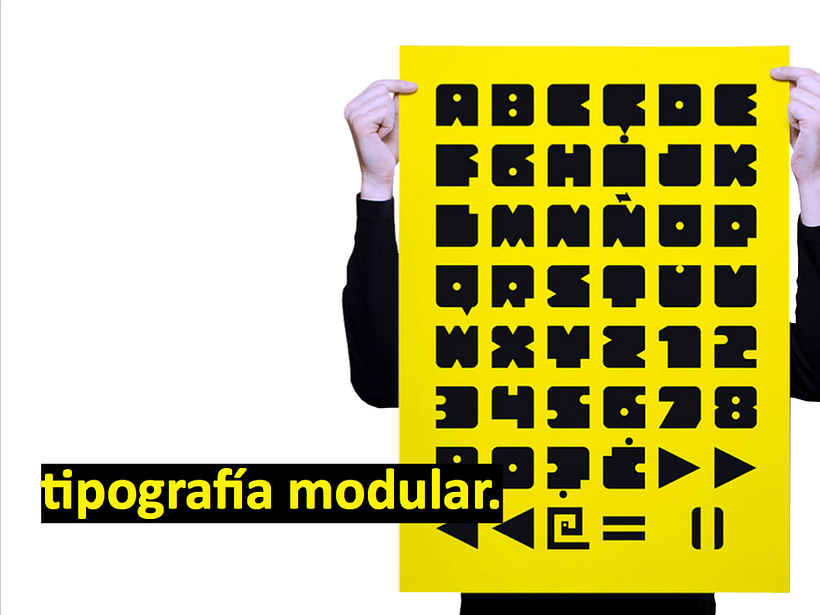
Tipografía modular
La tipografía modular consiste en construir alfabetos a partir de módulos y formas preconstruídas. Además, ofrece amplias posibilidades vinculadas a la comunicación del mensaje en el ámbito del diseño gráfico. Para Juan, es el punto de partida y la base inicial a la comprensión del mundo de la tipografía, así como la puerta a la formación de ideas en la imaginación o en el pensamiento del diseñador gráfico para la construcción de ideas más complejas.
El proyecto que Juan ha compartido es una recopilación de los trabajos de estudiantes que practicaron estas ideas de manera didáctica, con un carácter público y sin ánimo de lucro. Las tipografías finales fueron digitalizadas por ellos mismos con un programa online gratuito llamado Fontstruct.
Iris TTF
Por Iris Mogollón
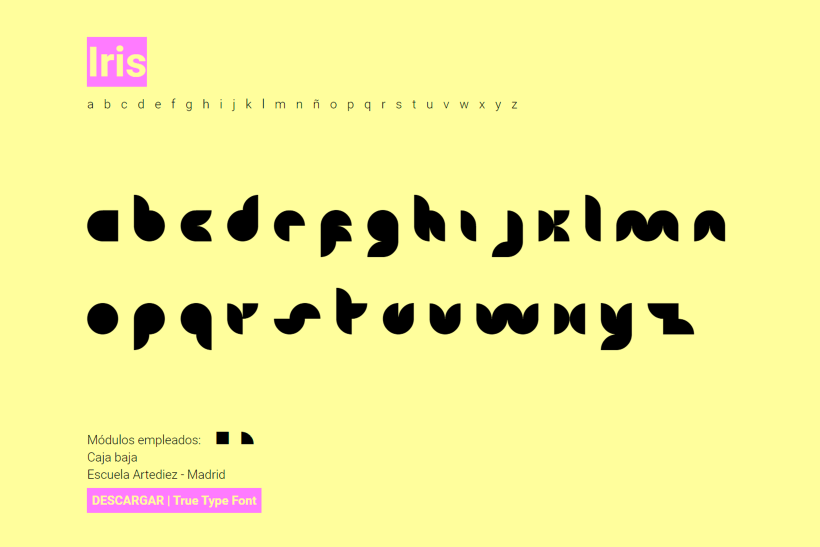
Cloven Regular TTF
Por Elena Gómez
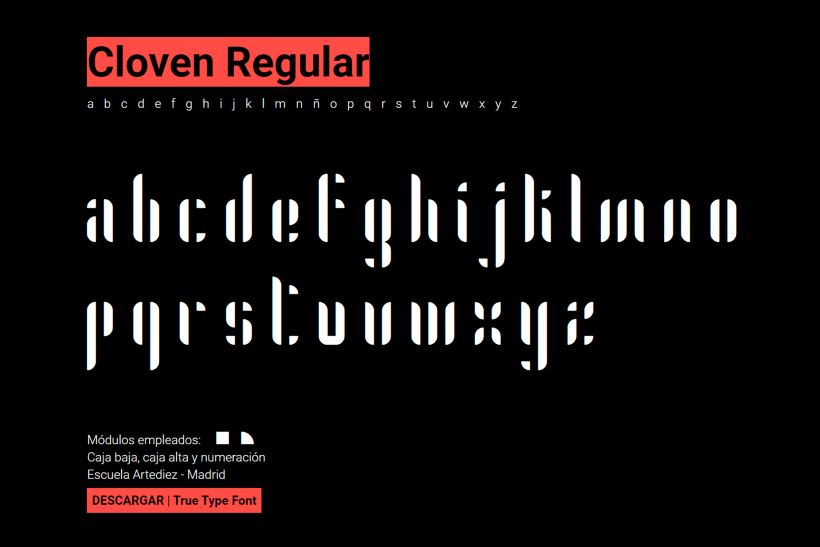
Cloven Bold TTF
Por Elena Gómez
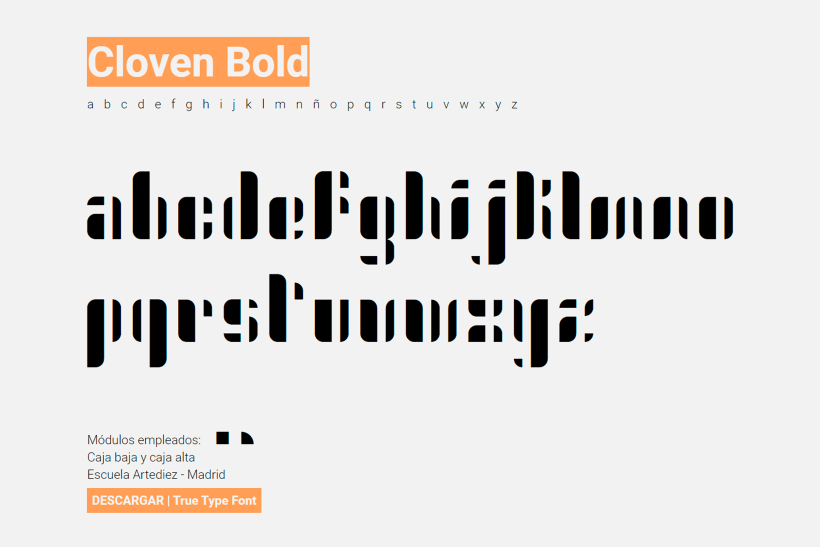
Mambo TTF
Por Cayetana Mate
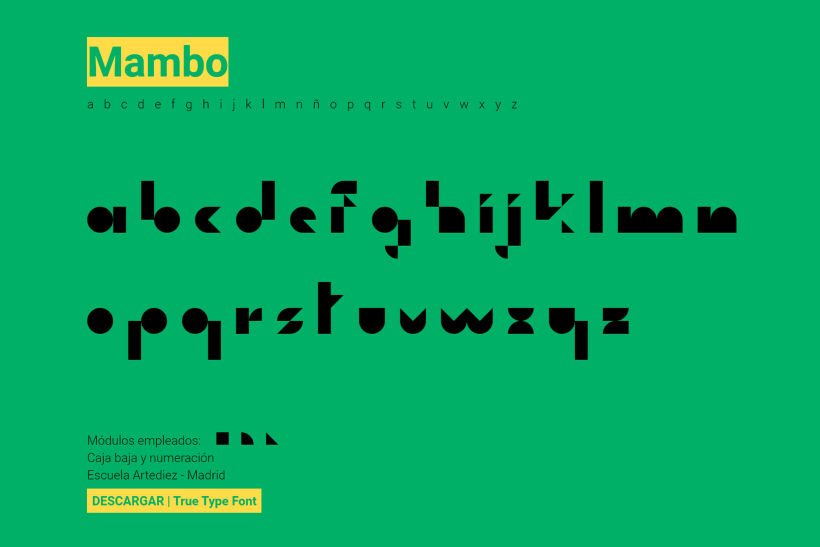
Land TTF
Por Alberto Navarro
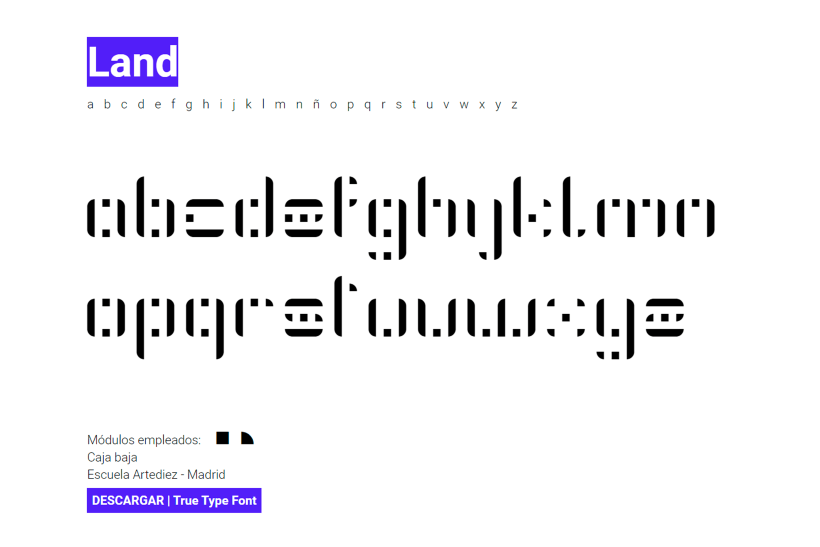
Building TTF
Por Mercedes Grande
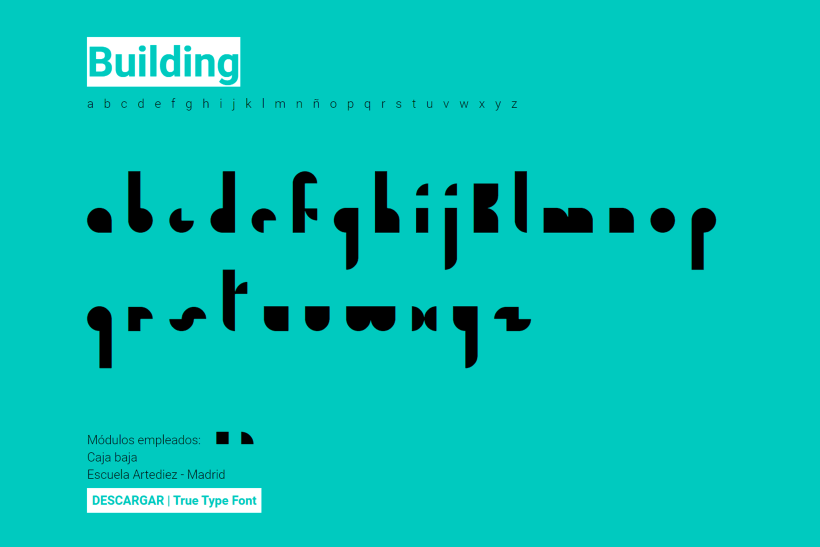
Thorn TTF
Por Alejandro Adrián Silva